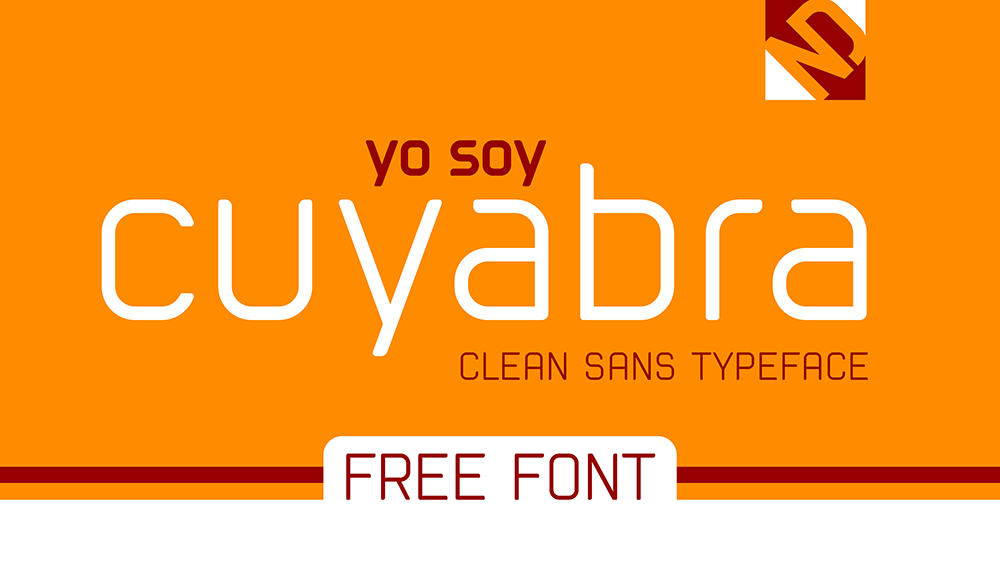
A Cuyabra Typeface é uma tipografia sans-serif que oferece uma aparência limpa e moderna. Seu design clean e elegante foi criado pelo designer Hamilton. Esta fonte é perfeita tanto para uso comercial quanto pessoal, com um download gratuito disponível para você explorar. É ideal para criar logotipos, flyers ou qualquer outro projeto gráfico em que uma tipografia minimalista se destaca. Compreender o valor de uma boa tipografia pode trazer uma grande diferença para seu próximo trabalho visual. A Cuyabra Typeface é a escolha perfeita para quem deseja estilo moderno e fácil de ler sem comprometer a estética.